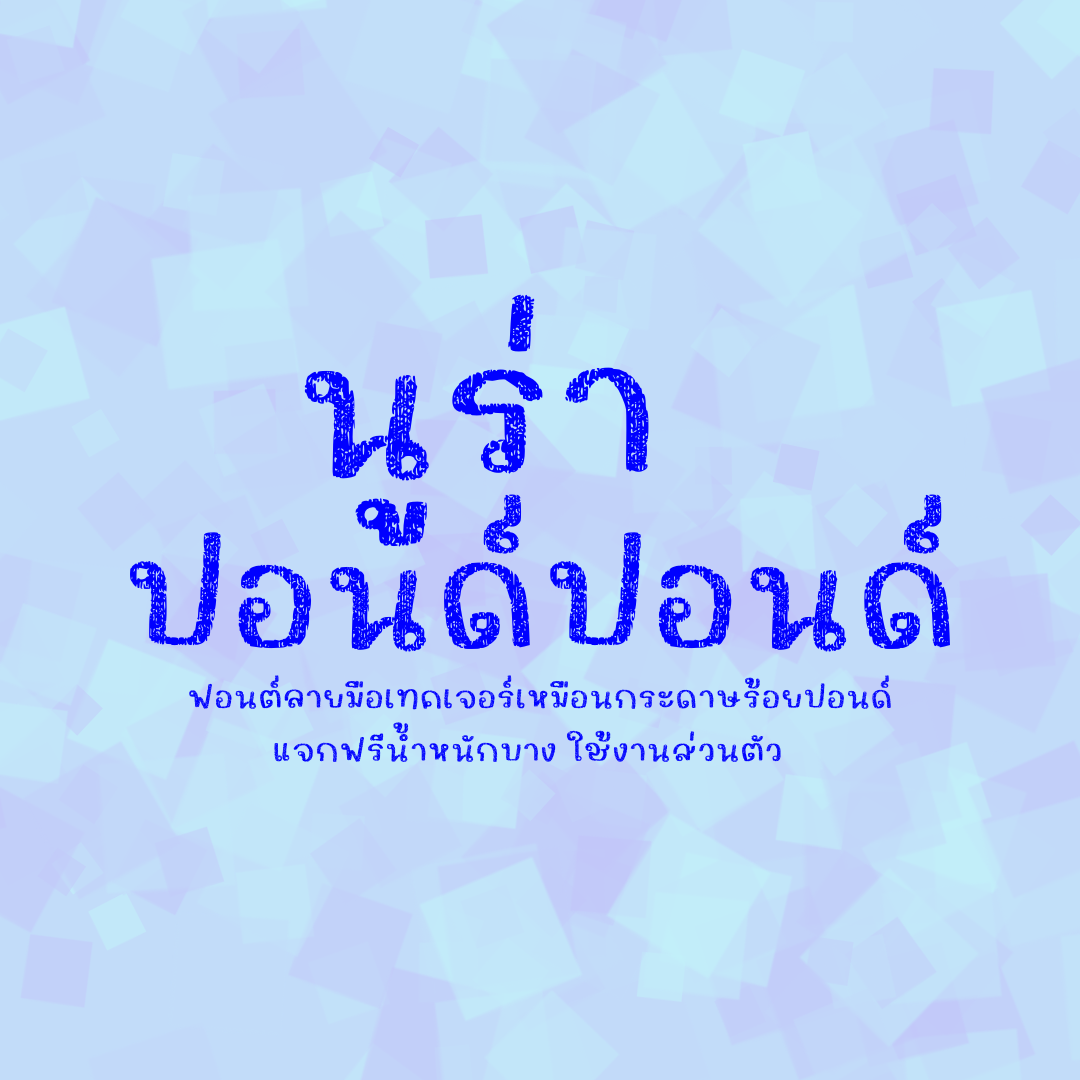
นูร่าปอนด์ปอนด์ (Nura pond pond)
ฟอนต์ลายมือเทคเจอร์กระดาษร้อยปอนด์  ฟอนต์มีด้วยกัน 3 น้ำหนัก คือ บาง ปกติ หนา   นูร่าราดาเปิดให้ใช้ฟรีส่วนตัว น้ำหนักบาง นะคะ